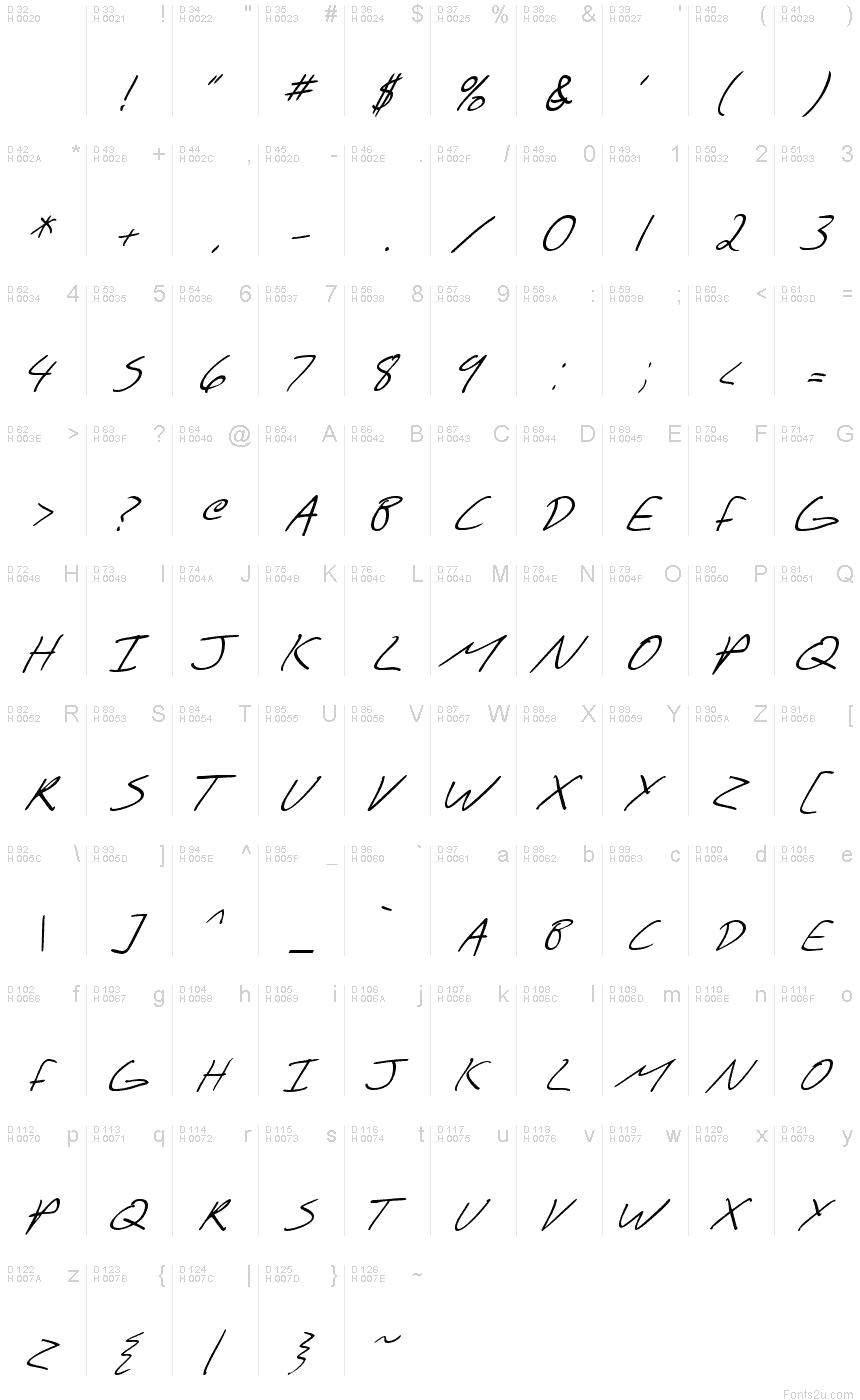
SF Scribbled Sans SC Italic od ShyFoundry to darmowy, odręczny krój kursywy, który ma w sobie swobodę szybkiego szkicu markerem. Wielkie litery pochylają się i tworzą pętle w długich, zwiewnych pociągnięciach, z luźnymi łączeniami i nagłymi akcentami, które sprawiają, że font wydaje się swobodny, improwizowany i celowo nieco niepokorny.
Świetnie sprawdza się na okładkach zinów, plakatach, grafikach na mixtape'y, notatkach na opakowaniach i planszach tytułowych, gdzie zbyt schludne pismo wyglądałoby zbyt wygładzonym. Jako darmowy font, dobrze też pasuje do krótkich nagłówków, inicjałów i monogramów, ponieważ te dynamiczne wielkie litery tworzą ruch, nawet gdy używasz tylko kilku znaków.
SF Scribbled Sans SC
ShyFoundry
Derek Vogelpohl